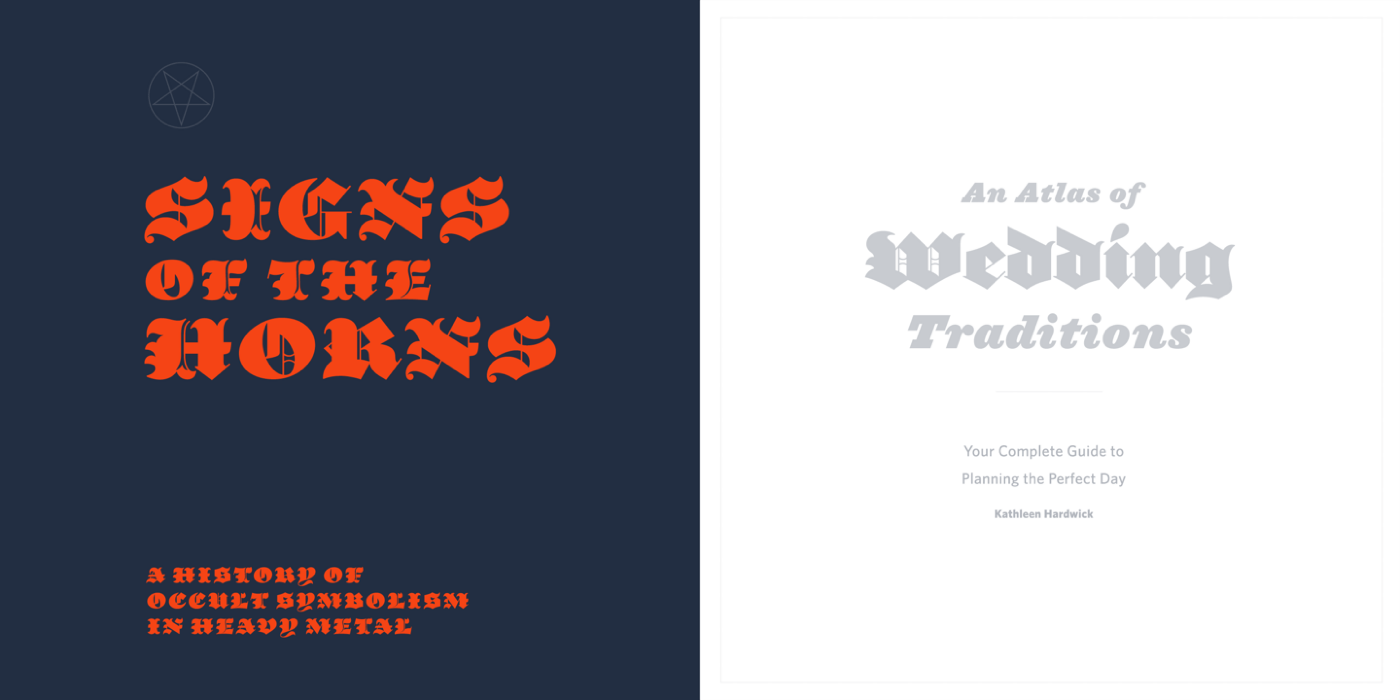
Die Parliament von Hoefler&Co. basiert auf einem fetten Schnitt der Gießerei Caslon aus dem 19. Jahrhundert. Die Entwürfe von Jonathan Hoefler gehen bereits auf das Jahr 1995 zurück. Die aktuelle Version in einem Schnitt mit Kapitälchen und Alternativzeichen wird vom Anbieter auf das Jahr 2022 datiert.